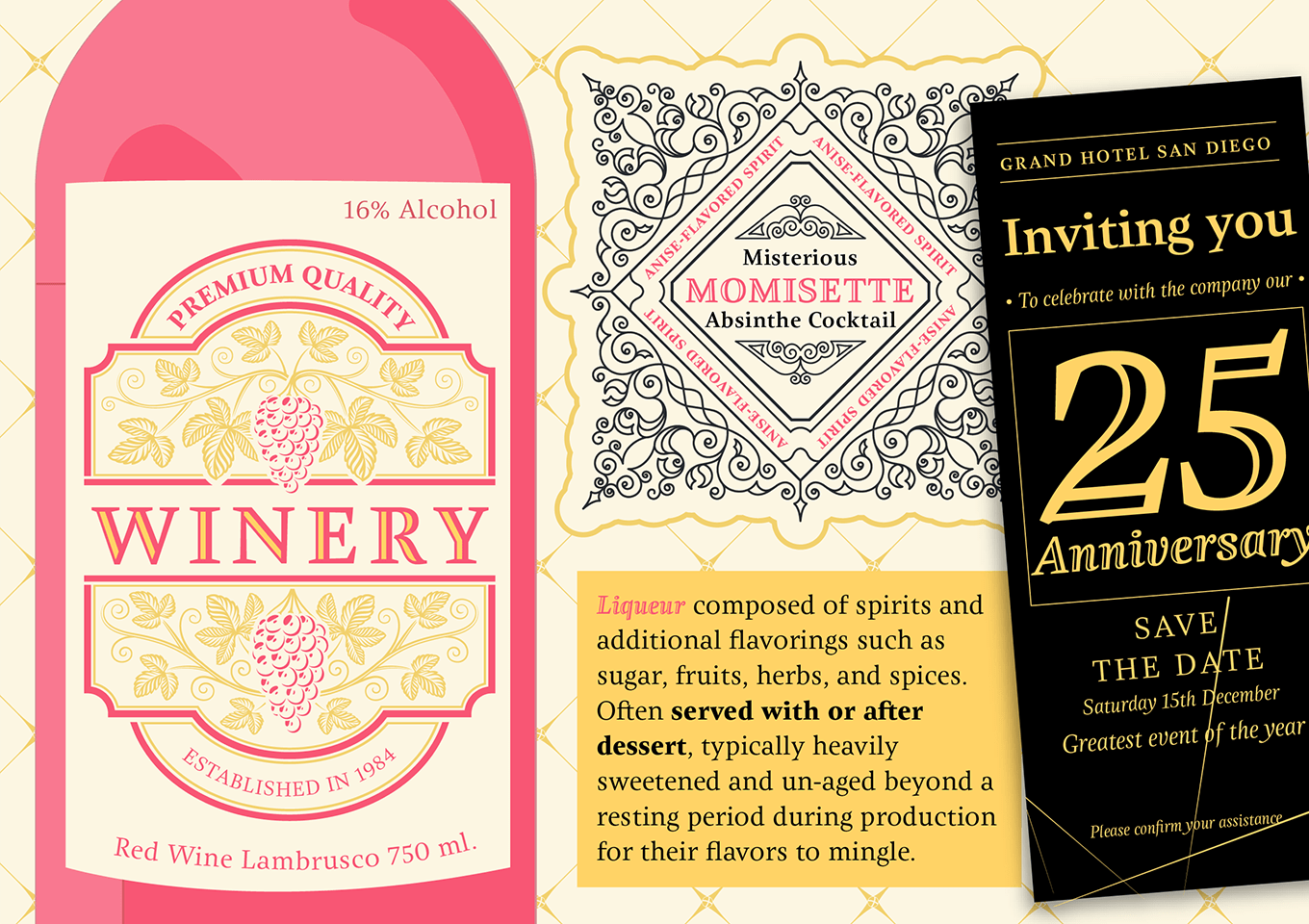
碑文に見られる伝統的なスタイルに自由な発想のデザインを掛け合わせたセリフ体です。エレガントでしなやかな骨格にやや無骨でエッジ感のあるエレメントを組み合わせることでユニークな表情を演出します。独創的でカリグラフィックなItalicや、装飾的な白抜き処理を施したスタイルも特徴の一つで、パッケージデザインや書籍装丁などのアクセントに最適な書体です。